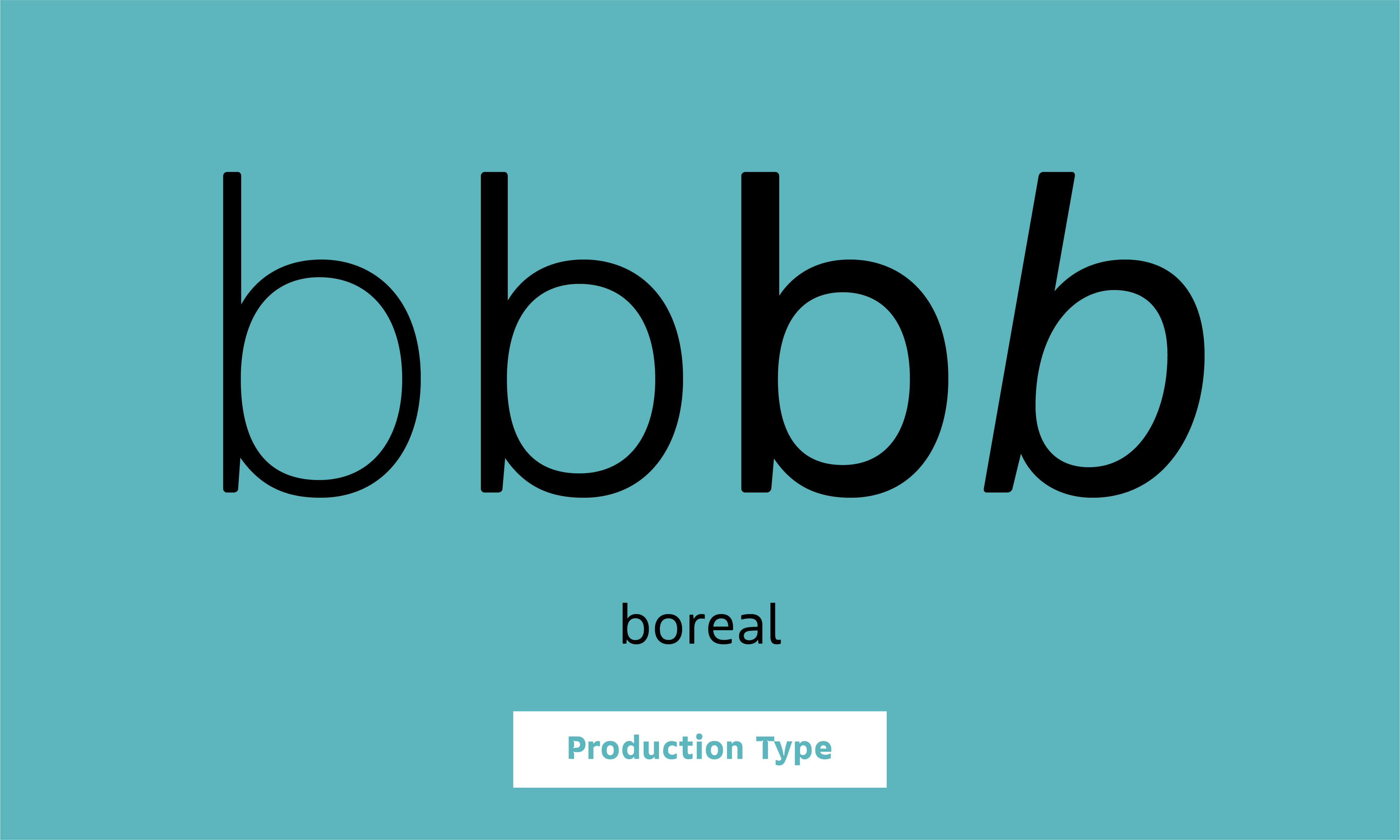
- Boreal은 캐나다 항공사인 Air Inuit를 위해 제작된 커스텀 폰트로 생기 있고 정감가는 산 세리프 계열의 폰트이다.
항공사의 정체성에 어울리도록 북부 퀘벡의 현지 이누이트족들의 언어를 표현할 수 있는 몇 안 되는 라틴 폰트이기도 하다.
깔끔한 형태를 갖고 있어 기업에서 만드는 자료나 UI 디자인에서 사용하기 좋다
폰트 정보 폰트명 Boreal 구분 명조 폰트디자인 Jean-Baptiste Levée, Mathieu Réguer, Quentin Schmerber, Marvin Harder